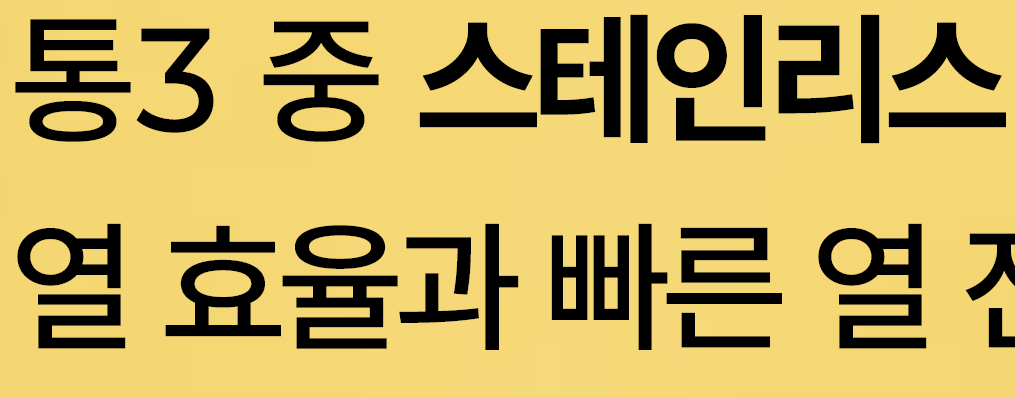
안녕하세요...혹시 아래 폰트가 뭔지 알 수 있을까요 ㅠㅜ 제발요
아래 폰트가 무슨 폰트인지 알아내야 쓸 수 있는데,
몰라서 3시간 째 헤매고 있습니다 ㅠㅜ
위아래 모두 프리텐다드 같고 굵기만 차이가 있는 것 같네요 https://www.sandollcloud.com/font/16951.html